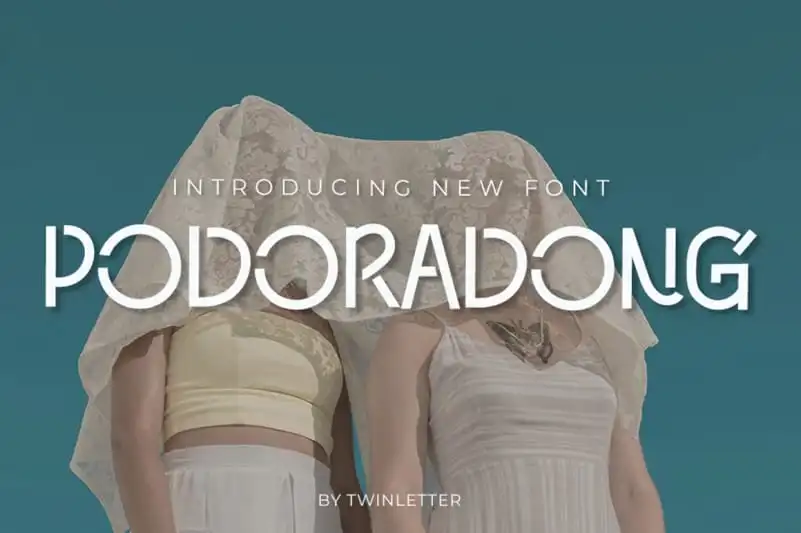
Podoradong Display Font – Download Grátis
Podoradong Display Font é uma fonte para exibição cuidadosamente criada com um toque elegante. Este é um combinado belo e sofisticado entre a elegância eterna e a autêntica caligrafia, mantendo sempre um ar de amabilidade. Podoradong traz uma estética clássica incrivelmente sólida, que se adapta perfeitamente para criar designs originais e destoantes. Este é o tipo certo para aqueles que buscam algo diferente na sua identidade visual, seja em logotipos, banners ou qualquer outro tipo de design gráfico.